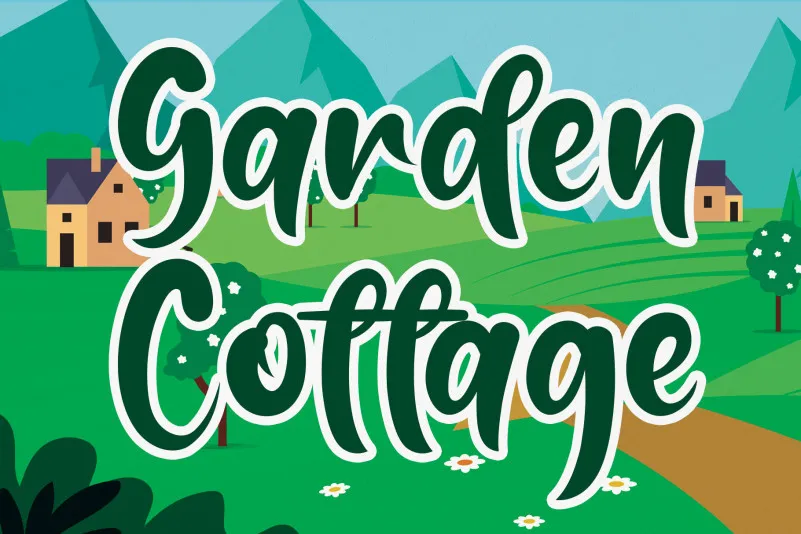
Garden Cottage Script Font é uma elegante fuente escrita à mão que traz um toque romântico e trendy. Com letras redondas e cheias de alegria, esta fonte é perfeita para criar cartões de aniversário ou convites de casamento com um toque pessoal e encantador. Seus traços suaves tornam qualquer design mais convidativo, adequado para aplicar em uma variedade de projetos decorativos como rótulos de pratos para festas caseiras, gráficos do Instagram personalizados ou até mesmo adesivos de plantação. Designada à medida da sua atmosfera acolhedora e autêntica, Garden Cottage Script Font é a escolha perfeita para quem deseja que seus designs falem por si mesmos com um toque amigável. A sua letra jovial e redonda cria uma atmosfera de conforto e felicidade que se adaptará a qualquer projeto. Numa época onde mais do que nunca, a personalização pode dar o arco final ao seu design, esta fonte escrita à mão não podia ser mais adequada para essa missão.